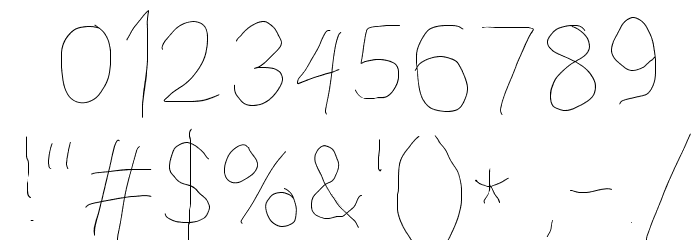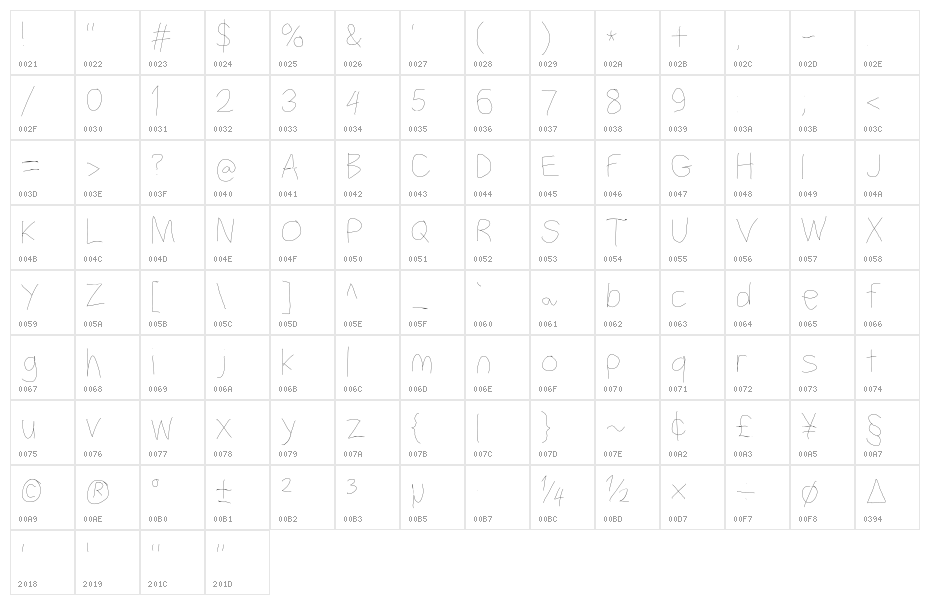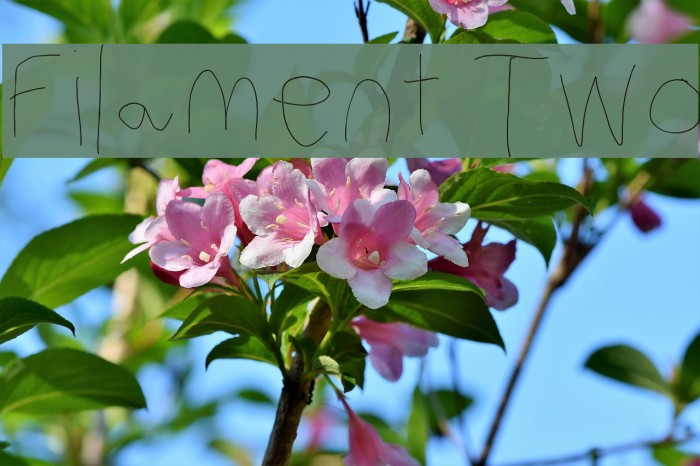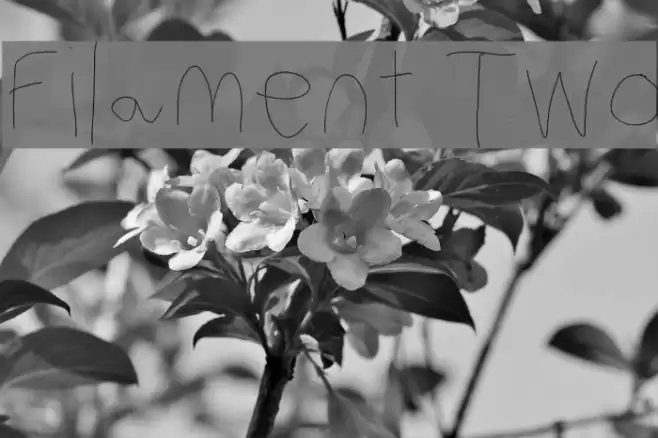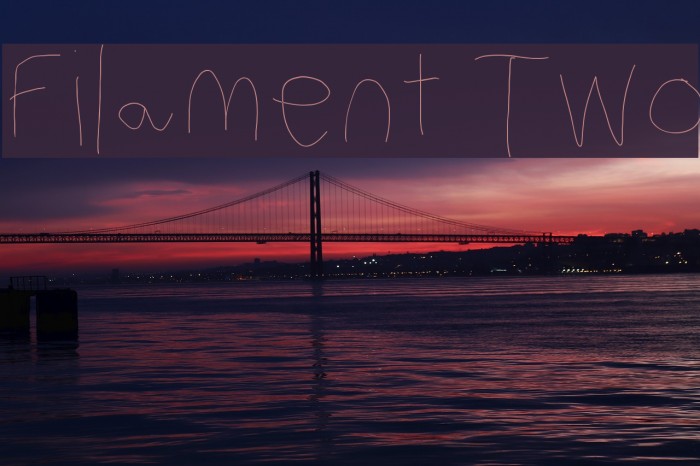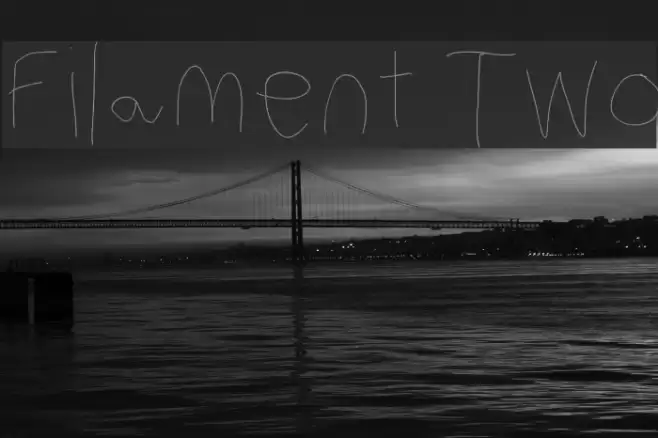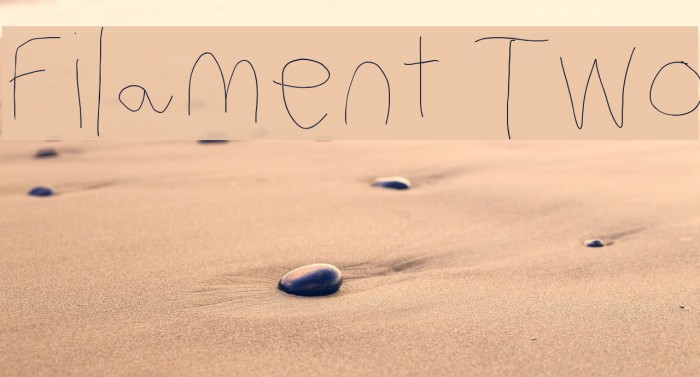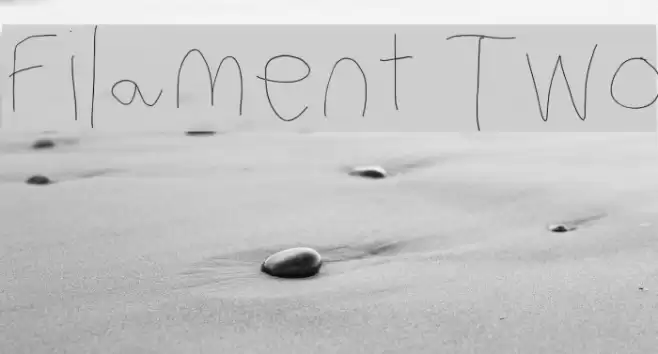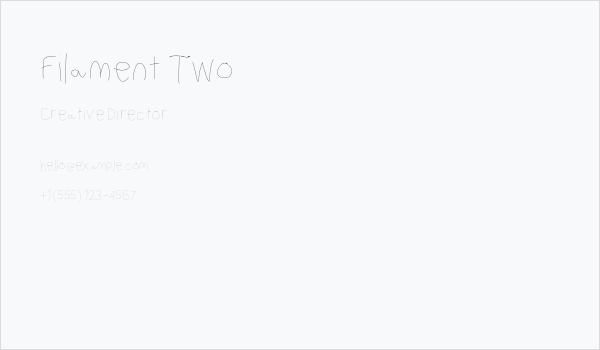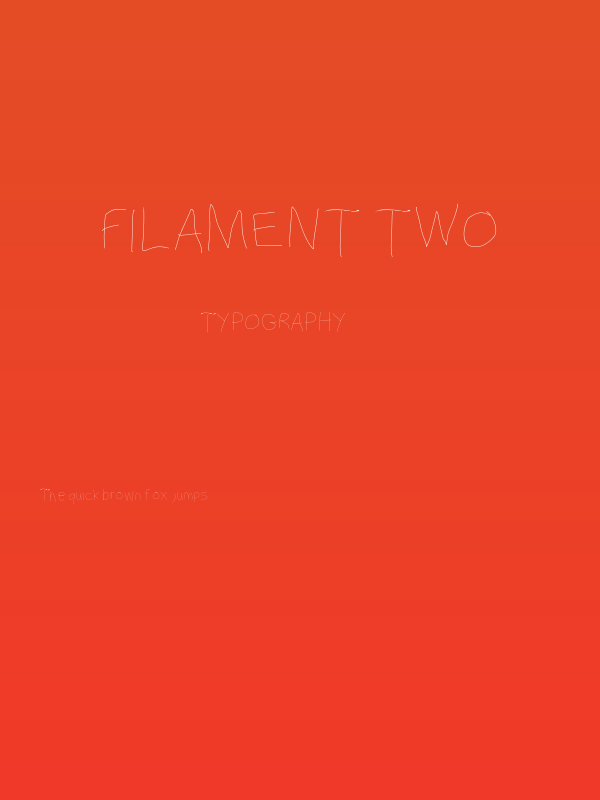
Filament Two Font
| Estilo general | Casual |
| Caso de uso | Headlines, Informal text, Personal projects |
| Proyectos propuestos | Ideal for personal notes, casual invitations, children's books, or any project needing a handwritten touch. |